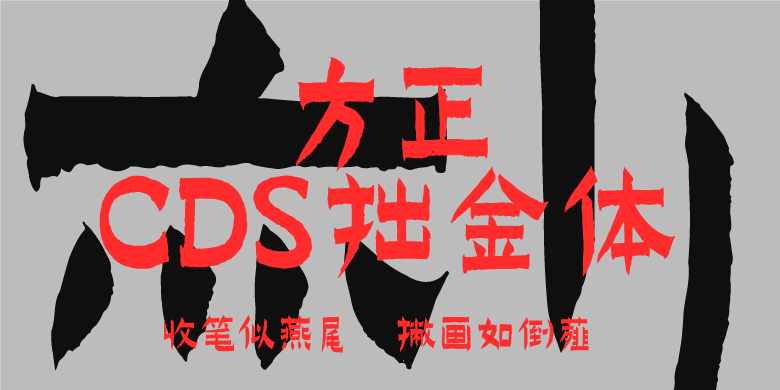
方正CDS拙金体
方正CDS拙金体,这款字体结构工整、笔画清晰,兼顾美观与易读性,适用于标题、正文、海报、包装、LOGO 等多种场景。字形优雅稳定,风格百搭耐看,适配日常排版与创意设计,让文字呈现更舒适、更具质感。方正CDS拙金体一笔一画,皆是细节,以均衡的比例、流畅的线条打造舒适视觉体验,字形端正大气,风格简约现代。无论是商业设计、品牌宣传还是日常排版,都能轻松驾驭,让文字更有格调与力量。方正CDS拙金体字体下载。
CDS拙金体CDS设计师沙龙作为一个公益组织一直以来致力于对中国传统文化美学研究与探索。艺术家耿晓刚先生多年尝试将中国积累沉淀的书法艺术文化推陈出新,面向当下想确立其新价值新意义。他亲笔的CDS拙金体就是将金农的书法书体“漆书”以现代人眼光再次呈现于当下。“漆书”是扬州八怪之首“金农”所创造的书法字体,它以其独特的风貌和意趣及精神内涵成为中国书法界不可或缺的经典之作;此书体特点以拙为妍,以黑为雅,横画粗、竖画细,起笔如蚕头、收笔似燕尾,撇画如倒薤,奇古仆拙之余又不失飘逸感, 此书体在历代书法史中具有极强的个性与学术性;同时此书的特性也合乎当下的审美趋势,如横画粗而不僵,厚而不肥,起笔突破了传统的蔵锋,而是先切笔然后行笔,简约干净利落,撇画具有曲线的美感,整体字形端庄优雅,大气简约,其字形也较符合一些作为标题、榜书、力求艺术特性的一些字体选择,同时也兼具内文的排版与特殊需求。
CDS除了一直致力于设计行业内外的经验分享与学术交流外,还踊跃探索东方语境下的文化美学,积极寻找其中的设计价值和哲学意义;本次CDS拙金体的设计,就是从中国书法文化中挖掘瑰宝,并结合当代审美理念,提炼出“金农漆书”的核心要素,进行重新创作设计,将中国的书法文化传承、创新与发扬光大。